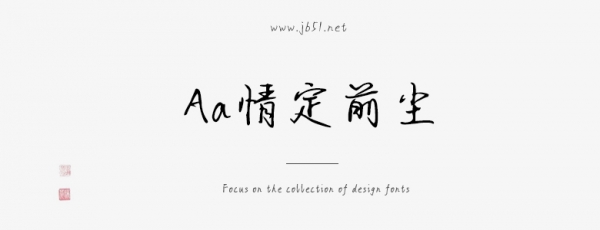
Aa情定前塵是一款不錯(cuò)的藝術(shù)字體,由Aa字庫出品,字體筆觸纖細(xì),書寫流暢 ,具有很好的視覺感,適合應(yīng)用于藝術(shù)設(shè)計(jì)、平面宣傳設(shè)計(jì)、網(wǎng)頁設(shè)計(jì),書法字帖等領(lǐng)域,需要的朋友可以前來本站下載。